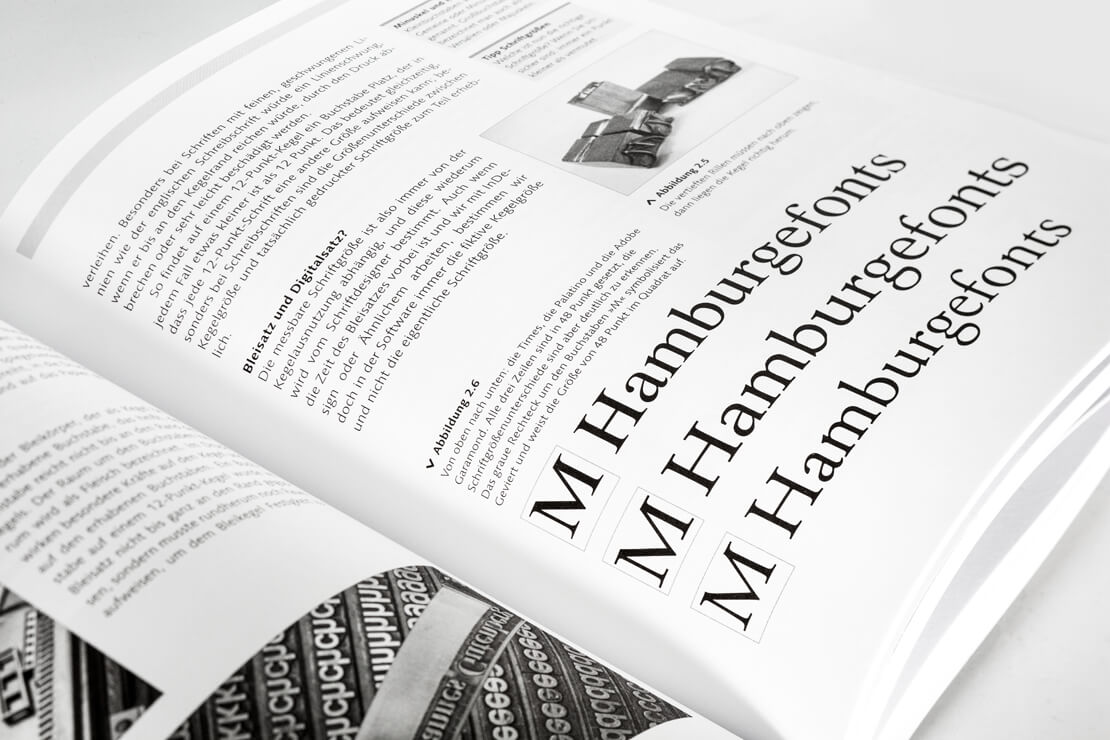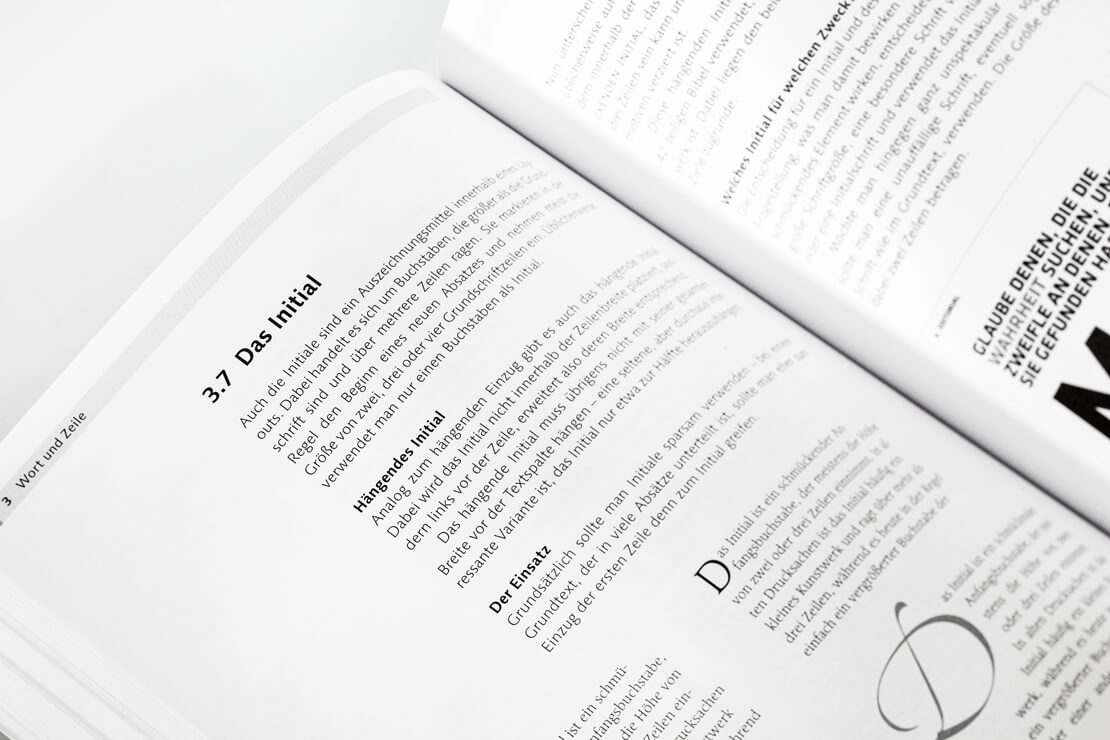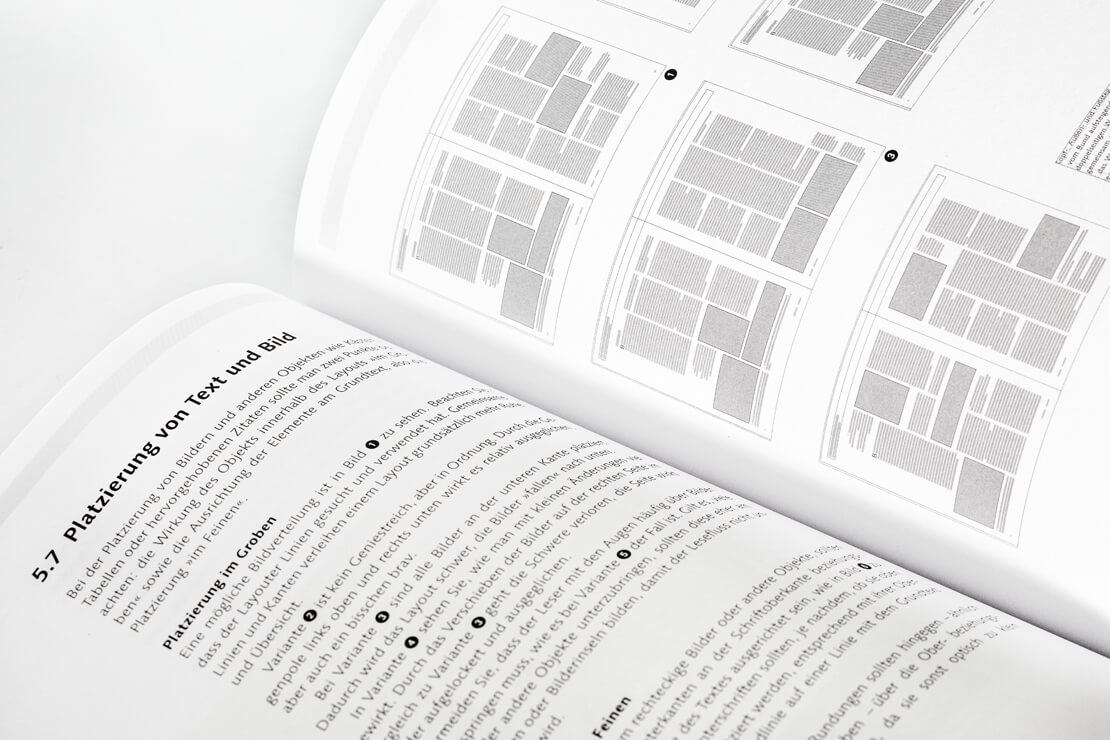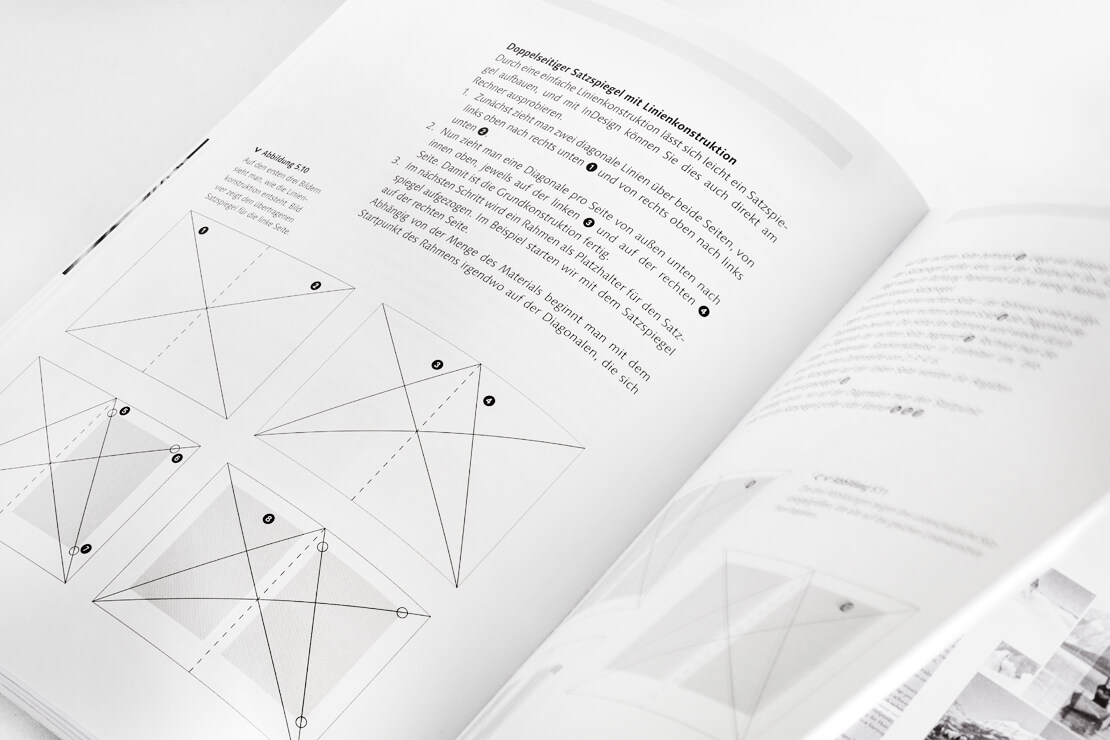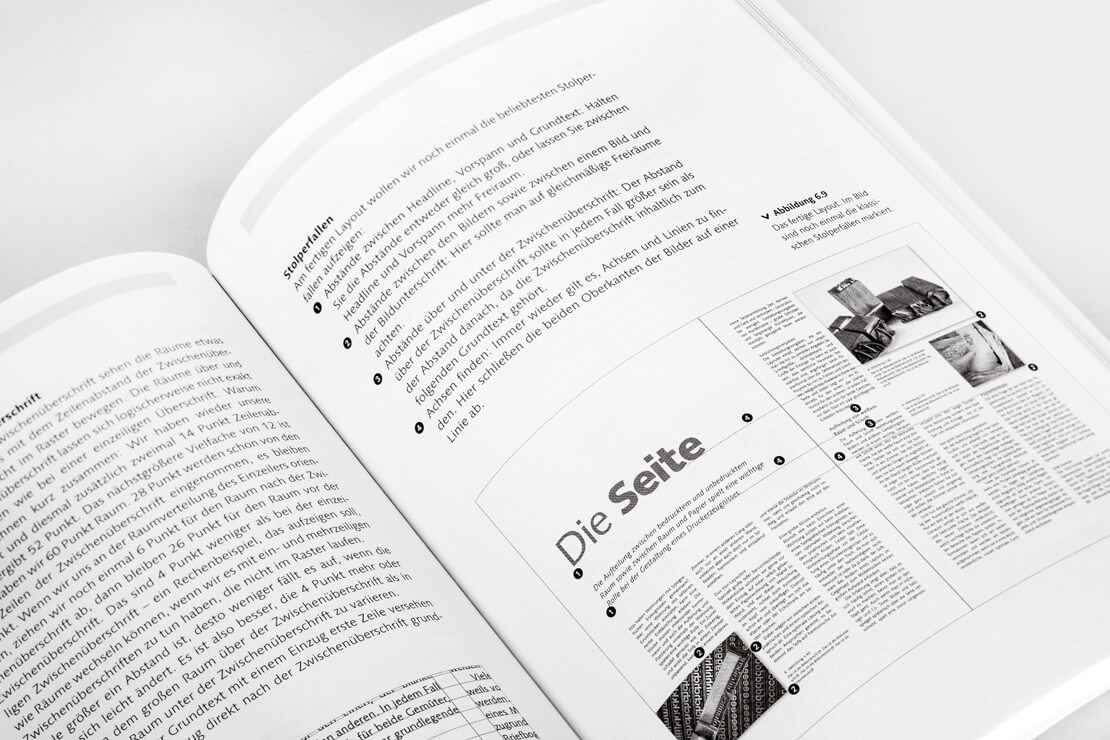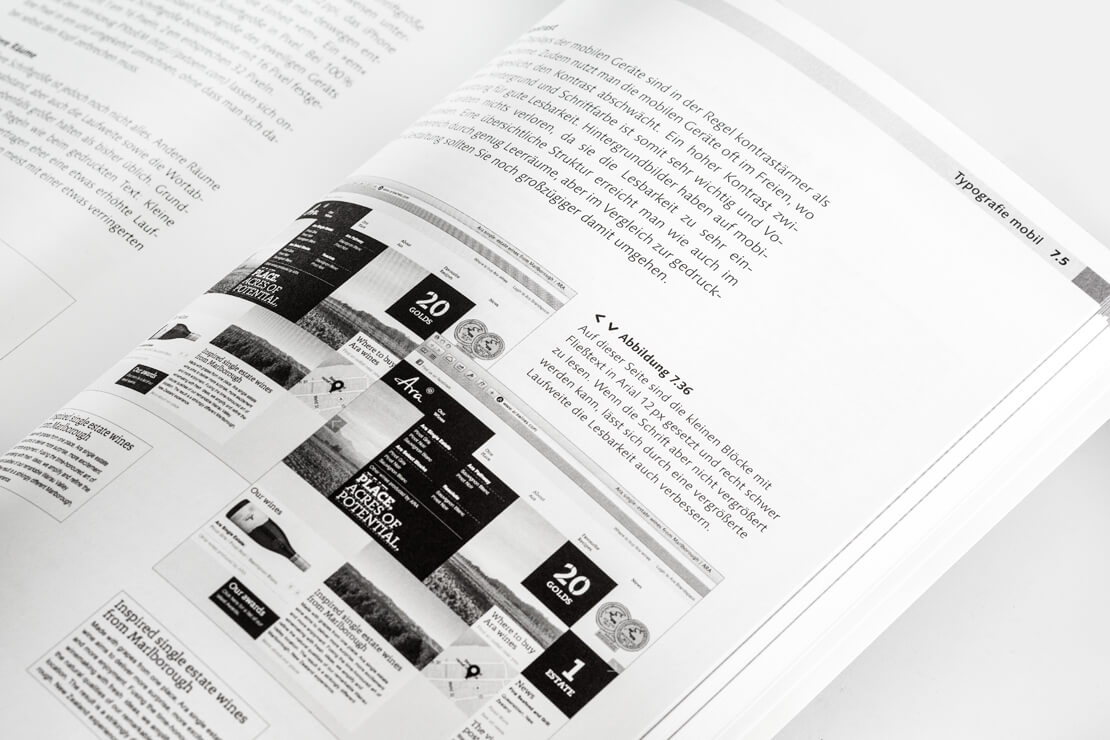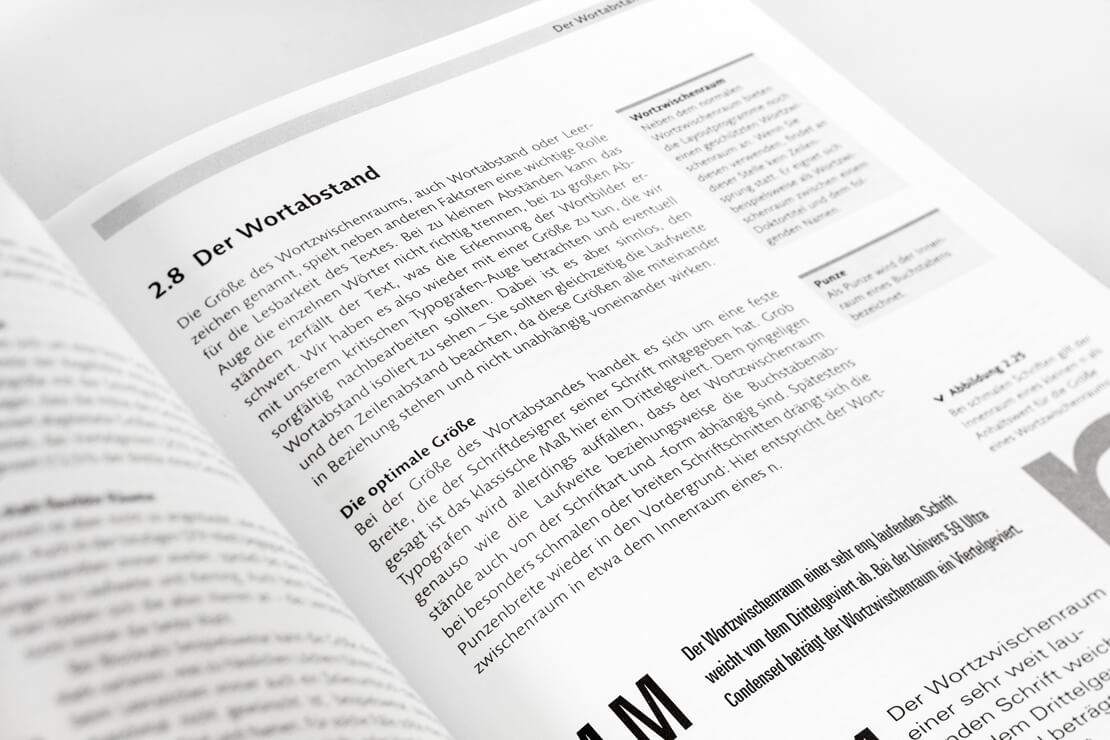
Grundkurs Typografie und Layout – für Ausbildung und Praxis
Seit fast 15 Jahren gibt es schon den »Grundkurs Typografie und Layout«. Mittlerweile liegt die sechste überarbeitete Auflage des Klassikers vor. Claudia Korthaus erklärt Konzepte und Begriffe der Typografie und veranschaulicht Regeln anhand von Praxisbeispielen.
Von der passenden Schriftwahl über Bild- und Textplatzierung bis hin zur Gesamtkomposition erfährt man hier Wissenswertes über Schrift und Schriftwirkung, Schriftklassifikation, Buchstaben, Wörter, Zeilen, Seiten, Papierformate, Mikrotypografie in InDesign und vieles mehr. Zudem zeigen viele Beispiele aus der Praxis, wie sich bereits mit kleinen Korrekturen große Wirkungen erzielen lassen.
Neben einem Exkurs in die Geschichte der Schrift und der Schriftentwicklung stellt das Kapitel »Schriftschnitt und Schriftfamilien« unter anderem bekannte Designer und ihre Schriftarten vor.
Was sich alles mit Buchstaben anstellen lässt, wird in einem eigenen, ausführlichen Kapitel beschrieben. Dort geht es beispielsweise um Serifen, Ligaturen, Wortabstände, Zeichenabstände und mehr.
Wichtige Informationen zu Ausrichtungsarten, optimaler Zeilenlänge, zum Zeilenabstand etc. erfährt man in »Wort und Zeile«. Die weiteren Kapitel des Buchs beschäftigen sich ausführlich mit Themen wie Satzspiegel, Gestaltungsraster, Platzierung von Text bzw. Bild und vieles mehr. Den Abschluss bilden Schwerpunkte zu Typografie im Web sowie Schrifttechnologien.
Ein umfangreicher »Index« führt gezielt zu Fachbereichen des Buchs. Somit eignet sich »Grundkurs Typografie und Layout« neben Studium und Ausbildung auch als Nachschlagewerk für die Praxis.